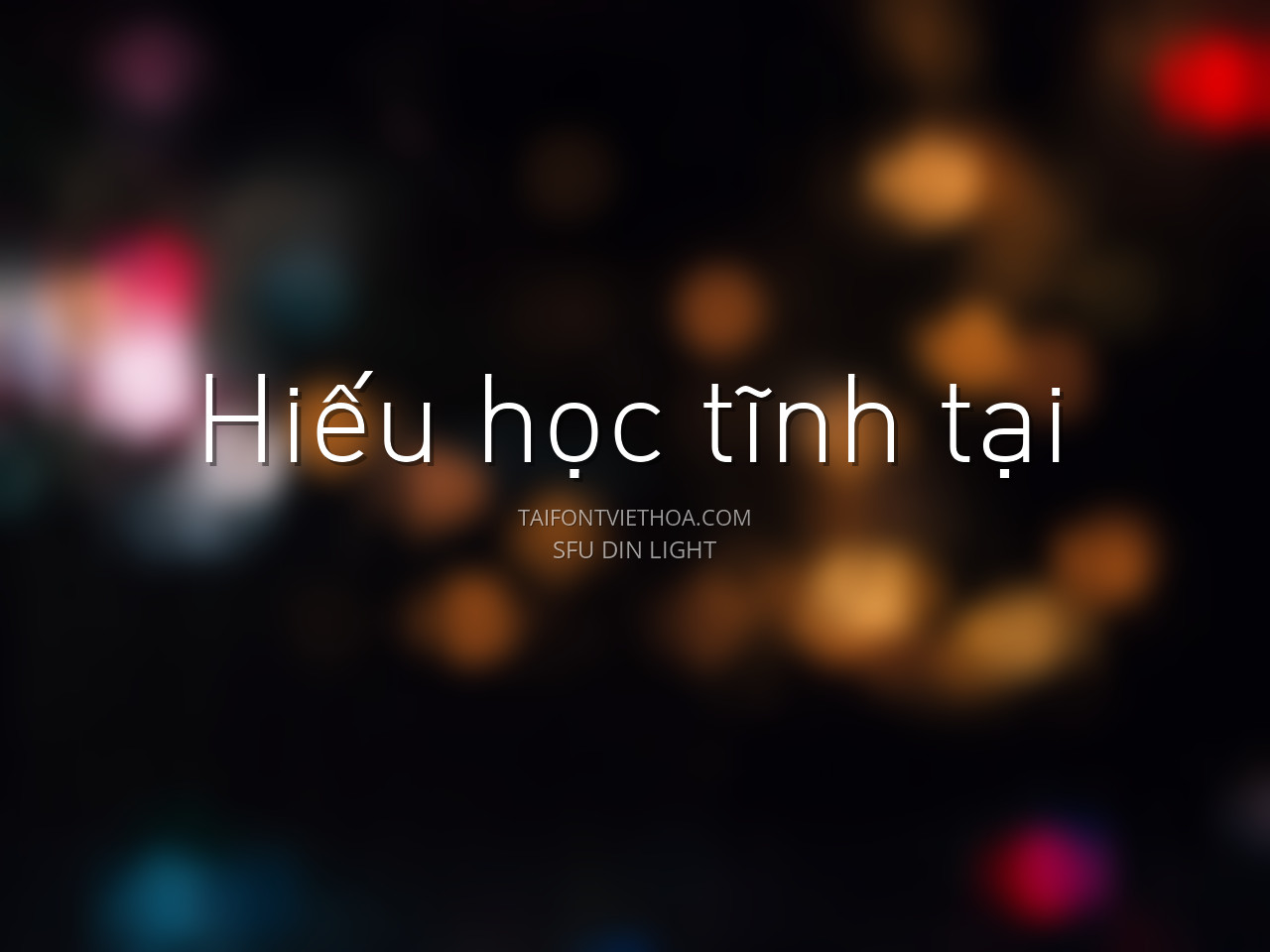
Font việt hóa SFU Dinlight
Giới thiệu về font SFU Dinlight – Kiểu chữ hiện đại chuẩn công nghiệp Đức
SFU Dinlight là phiên bản Việt hóa của DIN Light – một trong những biến thể nổi bật thuộc hệ thống font DIN (Deutsches Institut für Normung), được phát triển từ những năm 1930 cho mục đích kỹ thuật và công nghiệp tại Đức. Với thiết kế tối giản, chính xác và cực kỳ rõ ràng, DIN trở thành chuẩn mực không chỉ trong giao thông, mà còn lan rộng sang các lĩnh vực thiết kế thương hiệu và truyền thông hiện đại. Biến thể Light của DIN mang lại cảm giác tinh tế, nhẹ nhàng nhưng vẫn giữ được độ tin cậy vốn có của hệ chữ này.
Phiên bản SFU Dinlight đã được Việt hóa đầy đủ, hỗ trợ dấu tiếng Việt cùng hơn 100 ngôn ngữ khác. Taifontviethoa.comđã chọn lọc và chia sẻ font này như một giải pháp hoàn hảo cho những nhà thiết kế đang tìm kiếm một kiểu chữ sans-serif trung tính, chuyên nghiệp và thân thiện với giao diện hiện đại, đặc biệt phù hợp cho UI/UX và thiết kế thương hiệu kỹ thuật số.
Thiết kế tối giản, tinh tế và ứng dụng đa năng của SFU Dinlight
SFU Dinlight sở hữu cấu trúc sans-serif hình học gọn gàng, với tỷ lệ chữ cân đối, đường cong mềm và các góc tròn nhẹ. Biến thể Light giúp văn bản trông nhẹ nhàng, thoáng đãng và hiện đại hơn – rất phù hợp cho các thiết kế yêu cầu tính thẩm mỹ cao mà không đánh mất đi độ rõ ràng. Font cũng rất dễ đọc ở nhiều kích cỡ và định dạng hiển thị, đặc biệt tối ưu trong thiết kế kỹ thuật số.
Ứng dụng lý tưởng: thiết kế giao diện người dùng (UI), tài liệu doanh nghiệp, website, slide trình bày, nhãn bao bì sản phẩm công nghệ, hệ thống nhận diện thương hiệu và cả in ấn kỹ thuật. Ngành nghề phù hợp: công nghệ, kỹ thuật số, startup, tài chính, giáo dục hiện đại, bất động sản, kiến trúc và các doanh nghiệp hướng tới sự hiện đại và tối giản.